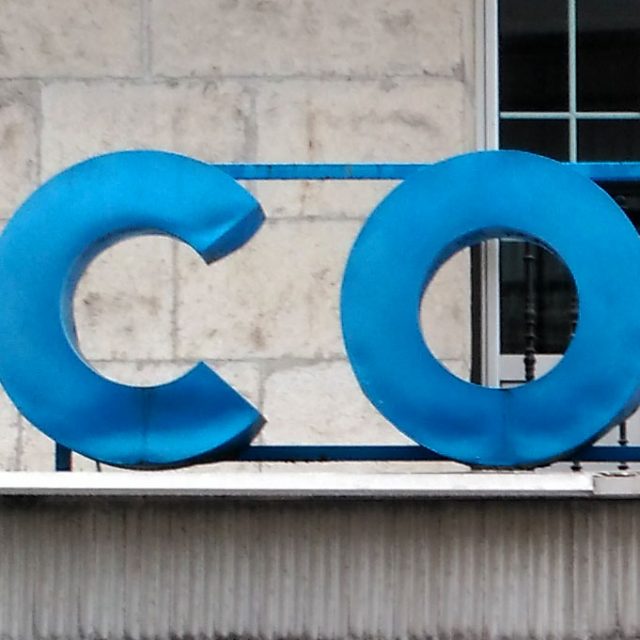
1908
Calle Isabel II, 3. Santander
Comercio familiar centenario de la ciudad, se abrió en 1908 en lo que era la Plaza de Atarazanas. Con motivo del Incendio de 1941 se trasladaron a la ubicación actual en la calle Isabel II.
Aunque en origen era una pequeña tienda con un rótulo en script, se fue ampliando hasta lo que hoy podemos ver. Dos grandes rótulos en azul en ambas entradas (Isabel II y Francisco de Quevedo) destacan en la fachada.